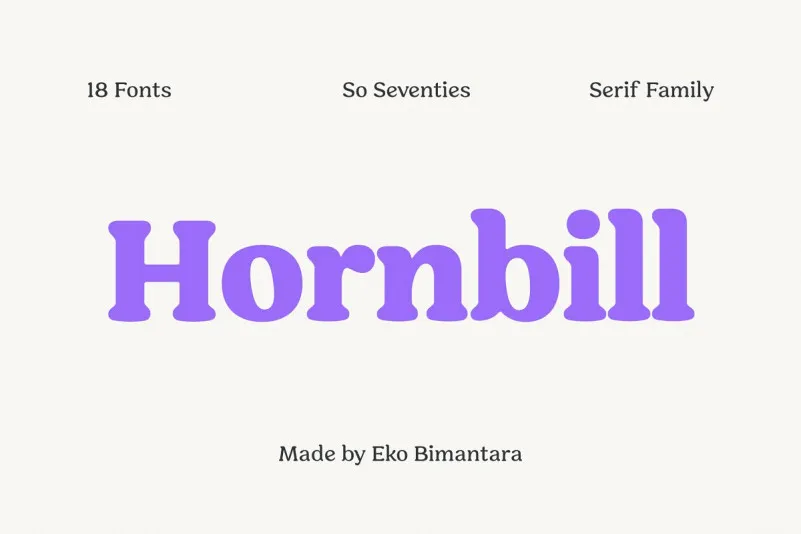
Esta é uma fonte serif suave chamada Hornbill Serif que cativa com seu estilo moderno e elegante, ideal para uso no design de títulos. Inspirada nos estilos retro dos anos 70, a Hornbill oferece um acabamento limpo e versátil para letras que se adaptam tanto ao design expositivo quanto à leitura. Com uma ampla gama de 18 tipografias variando do fino até o preto, cada uma se harmoniza perfeitamente com seu itálico complementar. Esta fonte da família Hornbill Serif é certamente a escolha ideal para designers que valorizam um equilíbrio entre sofisticação e modernidade.